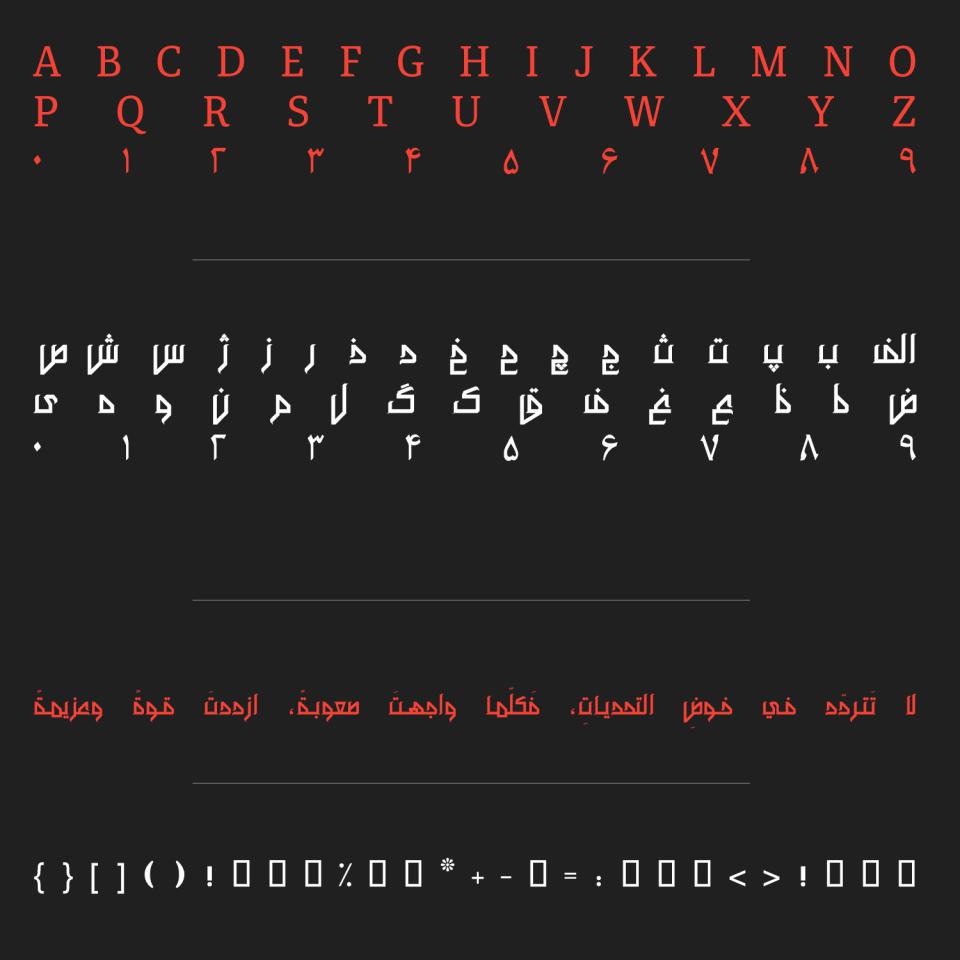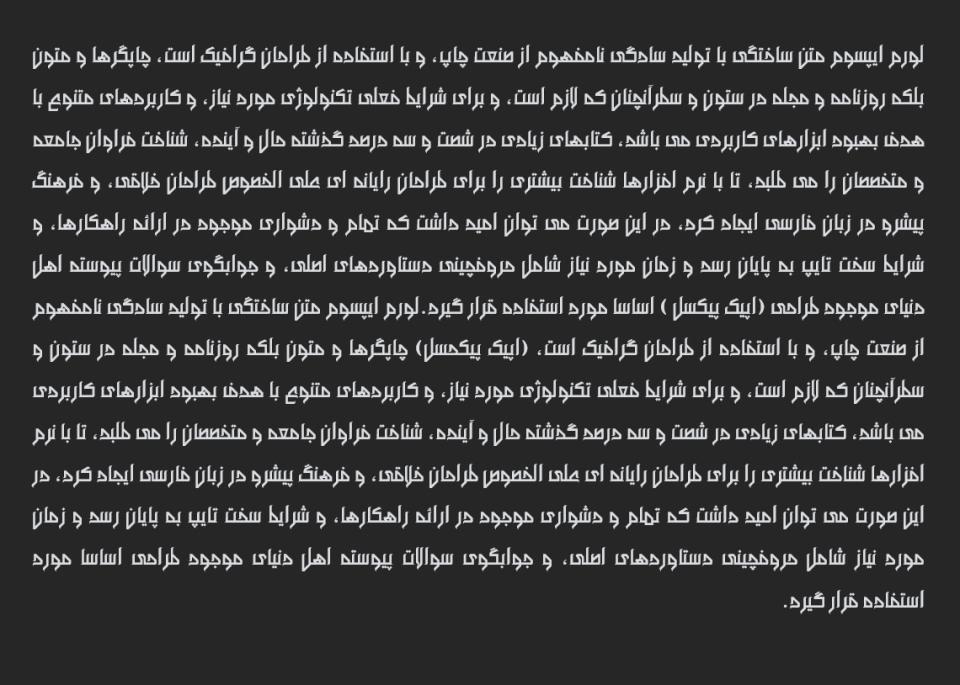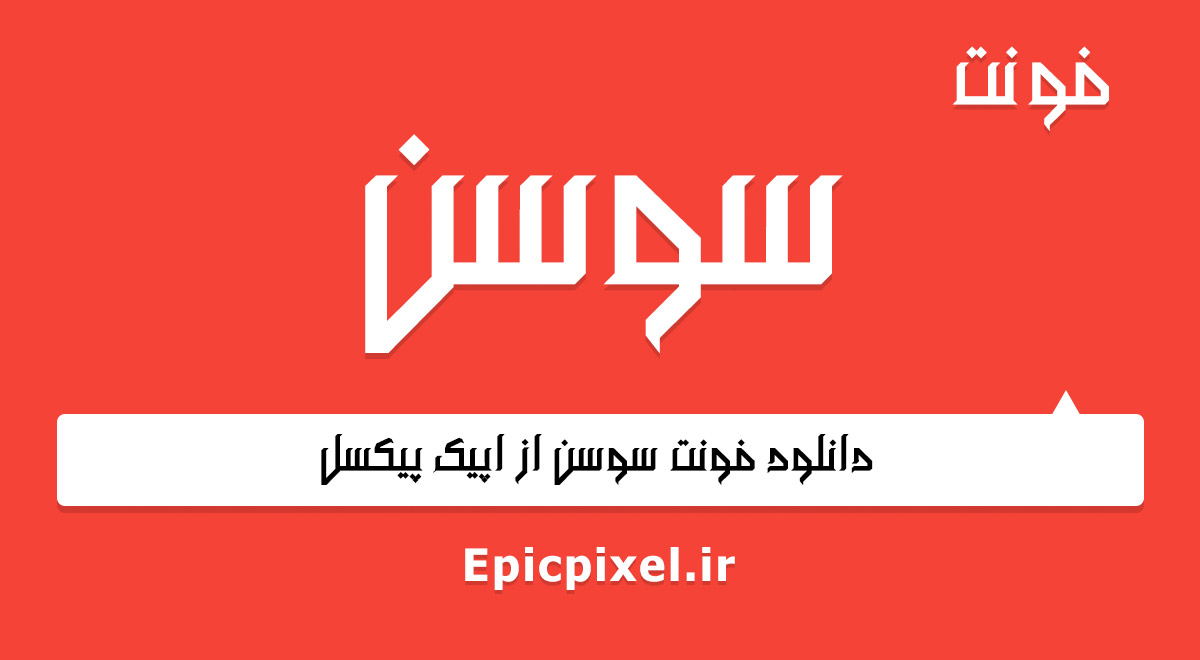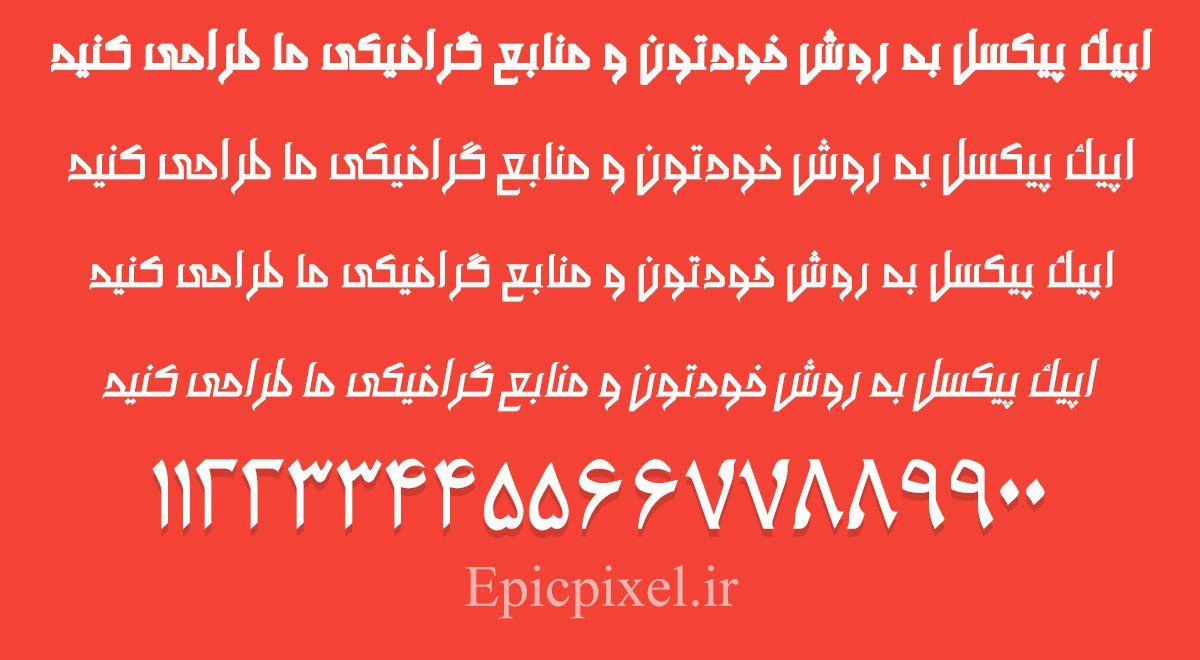
3 فونت سوسن فارسی
فونت سوسن فارسی، با طراحی ظریف و چشم نواز خود، جلوه ای خاص به نوشته های شما می بخشد. این فونت، که به صورت رایگان در دسترس است، با خطوط منحنی و هماهنگ، خوانایی متن را افزایش داده و تجربه ای لذت بخش از مطالعه را فراهم می کند.
یکی از ویژگی های برجسته فونت سوسن، طراحی منحصربه فرد حروف آن است که هم در متون طولانی و هم در عناوین کوتاه، زیبایی خود را حفظ می کند. این فونت با پشتیبانی کامل از زبان فارسی، تمامی حروف و نشانه ها را به درستی نمایش می دهد و هیچ گونه مشکلی در نگارش متون فارسی ایجاد نمی کند.
اگر به دنبال فونتی هستید که هم زیبایی بصری داشته باشد و هم خوانایی بالایی ارائه دهد، فونت سوسن فارسی انتخابی ایده آل برای شماست. این فونت، با طراحی مدرن و در عین حال کلاسیک خود، می تواند در طراحی های مختلف، از جمله وب سایت ها، کتاب ها، مجلات و پوسترهای تبلیغاتی، مورد استفاده قرار گیرد. پس همین حالا این فونت رایگان را دانلود کنید و به نوشته های خود جلوه ای تازه ببخشید.